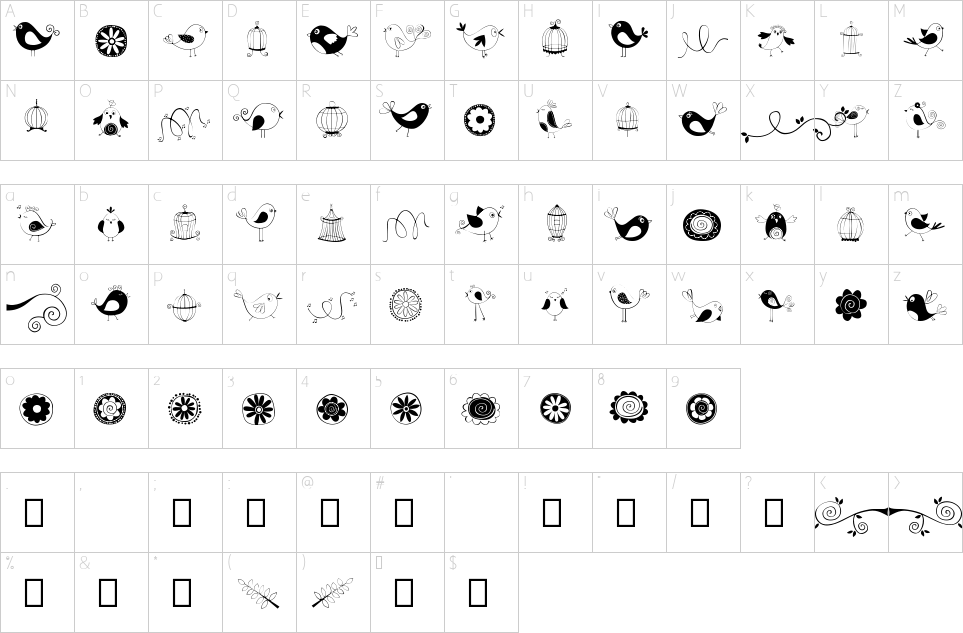
Doodle Dings 1 Birds Cages Font – Fonte Grátis
Doodle Dings 1 Birds Cages Font
Descubra Doodle Dings 1 Birds Cages, uma fonte única e artística que traz vida e criatividade a seus projetos digitais. Com origem na imaginação brilhante de Emily Spadoni, essa font oferece um toque diferenciado para qualquer projeto gráfico ou design digital. Ideal para aqueles que valorizam estilos únicos e desenhos complexos, Doodle Dings 1 Birds Cages é uma escolha ideal para designers buscando um elemento personalizado em seus trabalhos. Com downloads consolidados a 25,579 vezes, essa font tem se destacado como uma opção não apenas gratuita, mas também de alta qualidade. Com o Doodle Dings 1 Birds Cages Font, você pode explorar formas criativas e estilos artísticos sem comprometer os recursos do seu projeto. Seja para adicionar um toque de diversão a sua logo ou criar um design único que destaca-se em qualquer plataforma digital, essa font é uma escolha inteligente para aqueles buscando novos recursos gráficos. Descubra o potencial desta font e transforme seu trabalho em algo ainda mais especial. Com Doodle Dings 1 Birds Cages Font, sua criatividade pode voar.